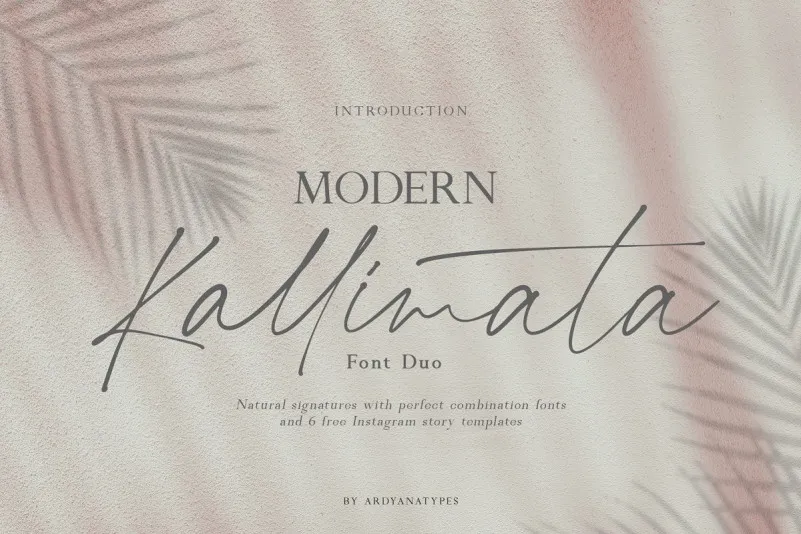
Modern Kallimata Font Duo – Download Grátis
Modern Kallimata Font Duo é uma escolha perfeita para designers que procuram uma combinação única entre a elegância dos caracteres script e a modernidade dos serifos. Este duo de fontes, criado pela M.0Type, foi projetado especialmente para aplicação em marcas, assinaturas, logotipos ou qualquer outra necessidade de design moderno. O estilo de Modern Kallimata é contemporâneo, proporcionando uma combinação arrojada entre os elementos script e serif, resultando em um resultado visualmente atraente e sofisticado. O que torna Modern Kallimata Font Duo ainda mais especial são suas características naturais. A fonte incorpora riscos de mão, dando um toque natural às letras. O design inclui dois estilos principais: Script e Serif. Kallimata Script apresenta uma textura muito natural, com aparência de manchas naturais em cada criação visual, enquanto Kallimata Serif é projetado para complementar a script para torná-las ainda mais sofisticadas. Além disso, o duo vem acompanhado por alternativas que adornam cada risco da fonte. O design de Modern Kallimata é perfeito para aplicação em trabalhos gráficos como posters, assinaturas, logotipos, capas de álbuns, cartões de negócio ou qualquer outra necessidade. As características do script têm um toque único e elegante, tornando-o fácil de ler e memorizar, além de ser facilmente usável em qualquer projeto gráfico. Esta font é uma excelente opção para designers que buscam adicionar um toque sofisticado a seus trabalhos.